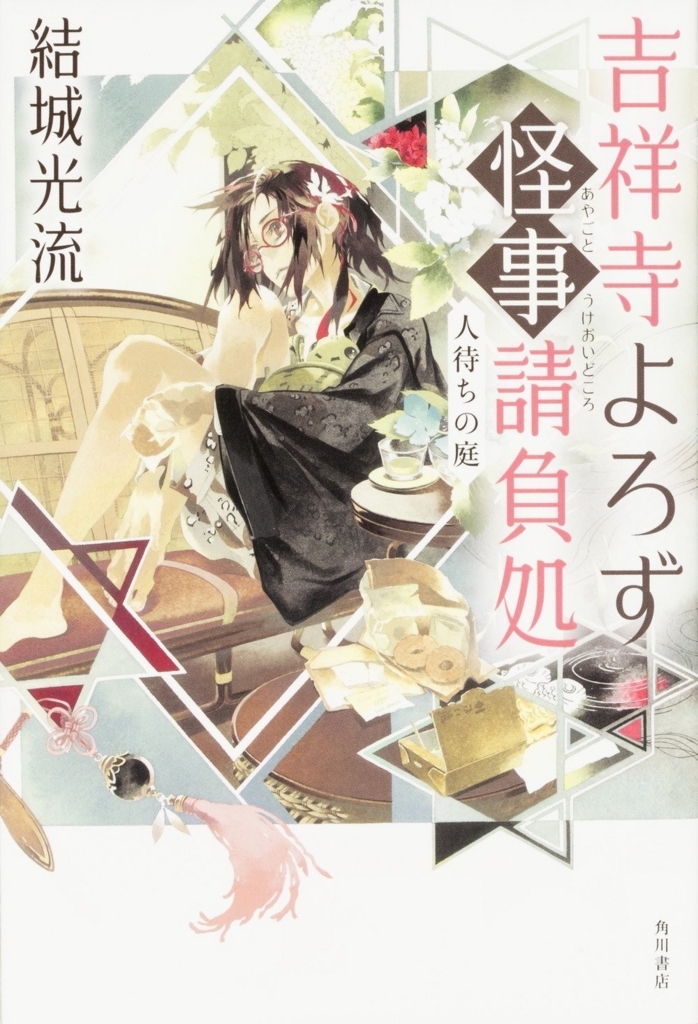
吉祥寺よろず怪事請負処 人待ちの庭
吉祥寺よろず怪事請負処 人待ちの庭のタイトルのフォントに娥眉明朝体が採用
角川書店「吉祥寺よろず怪事請負処 人待ちの庭」のタイトルにダイナフォントの娥眉明朝体が採用されている。
娥眉明朝体
通常の明朝体をベースに細長く弧を描いた眉の形をイメージしたストロークから洗練された女性の柔らかさや優しさを表現している。女性用品などのロゴやキャッチコピーに特にオススメの書体であり、女性の美しさを追求した明朝体として、清潔感や高級感ある商品の演出などに優れている。